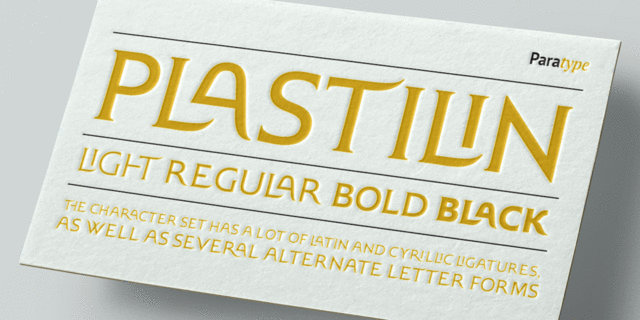
Гарнитура Пластилин в двух начертаниях получила своё название благодаря мягким, изогнутым окончаниям некоторых знаков (J, K, L, R и др.) и небольшим острым засечкам, как бы вытянутым из пластичной массы штрихов. Гарнитура имеет большое количество нестандартных латинских и кириллических лигатур, а также несколько альтернативных букв. Пластилин разработан для компании ПараТайп в 2005 году Олегом Карпинским. Предназначен для акцидентных надписей и небольших текстовых блоков. В 2008 году автор дополнил шрифт светлым и сверхжирным начертаниями с корректировкой формы некоторых знаков.